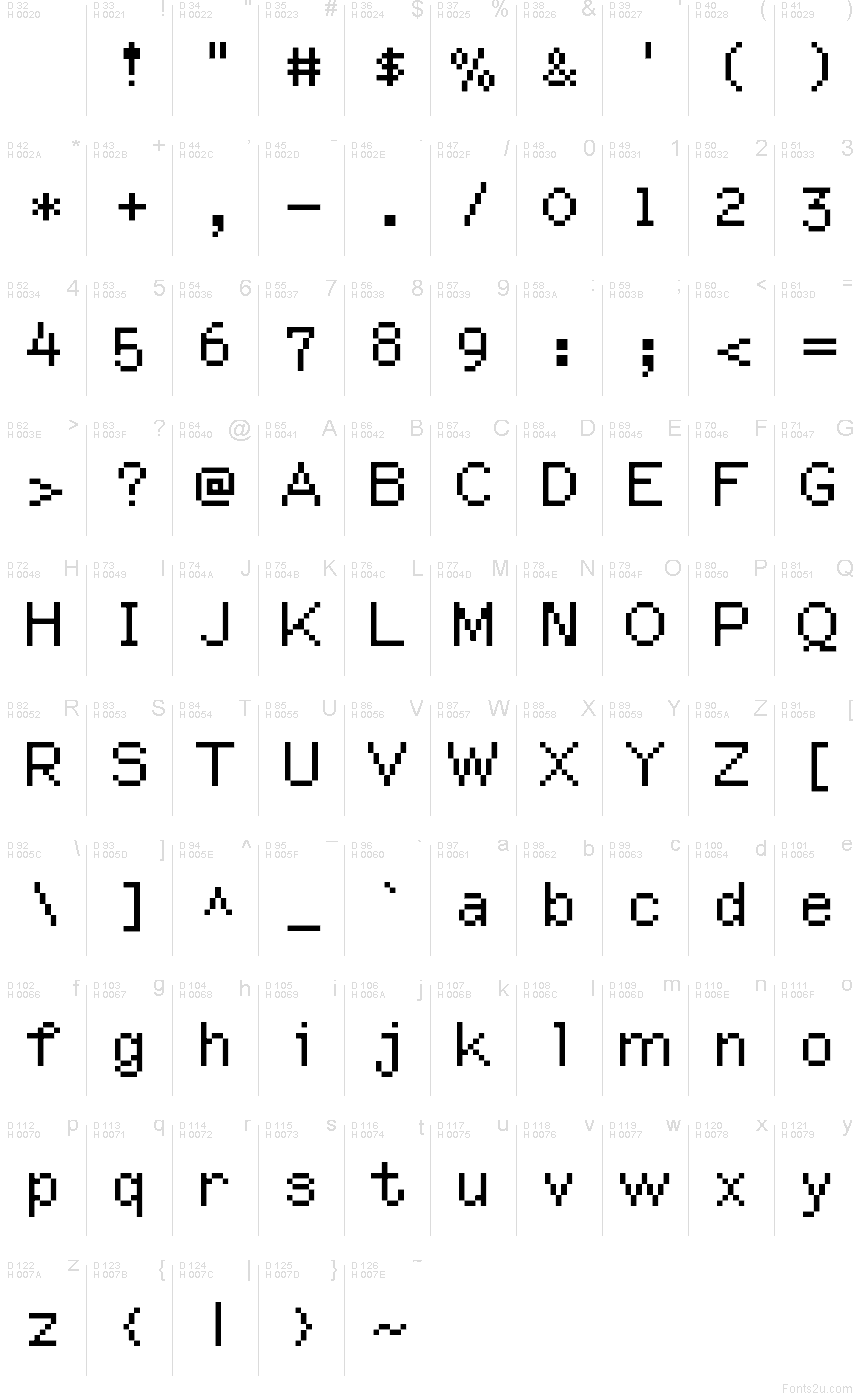
Deer Diary, da MagicBear, é uma fonte pixel bitmap gratuita com aquele toque suave de diário de computador antigo. As suas letras quadradas e robustas mantêm a grelha visível, mas os cantos arredondados e as ligações ligeiramente irregulares conferem-lhe um aspeto mais manuscrito do que mecânico, como notas digitadas no ecrã de um antigo dispositivo portátil.
Esta mistura é perfeita para interfaces de jogos, fanzines, autocolantes, títulos de cartazes e branding com estilo de diário, onde uma fonte gratuita pode trazer um toque retro suave sem se tornar agressiva ou demasiado arcade. Funciona melhor em frases curtas e títulos, porque a sua textura em bloco e as suas pequenas peculiaridades conferem até às palavras simples um tom pessoal, como se fosse um lembrete.
Fonte pixel sem serifa criada com Fontstruct.